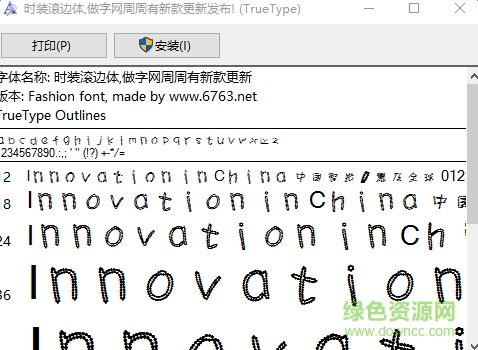
時(shí)裝滾邊體
時(shí)裝滾邊體是一款很不錯(cuò)的電腦藝術(shù)字體有著獨(dú)特的藝術(shù)風(fēng)格,用于廣告設(shè)計(jì)、藝術(shù)設(shè)計(jì)等方面再合適不過了,當(dāng)然如果大家喜歡這款字體不管用在什么方面都是可以的,歡迎大家來綠色資源網(wǎng)下載。